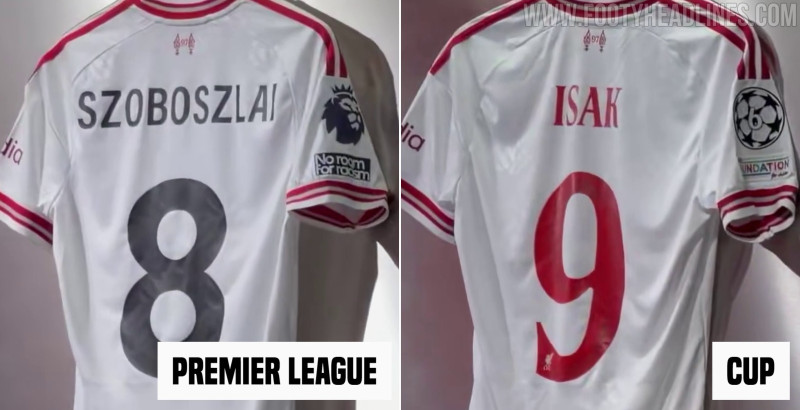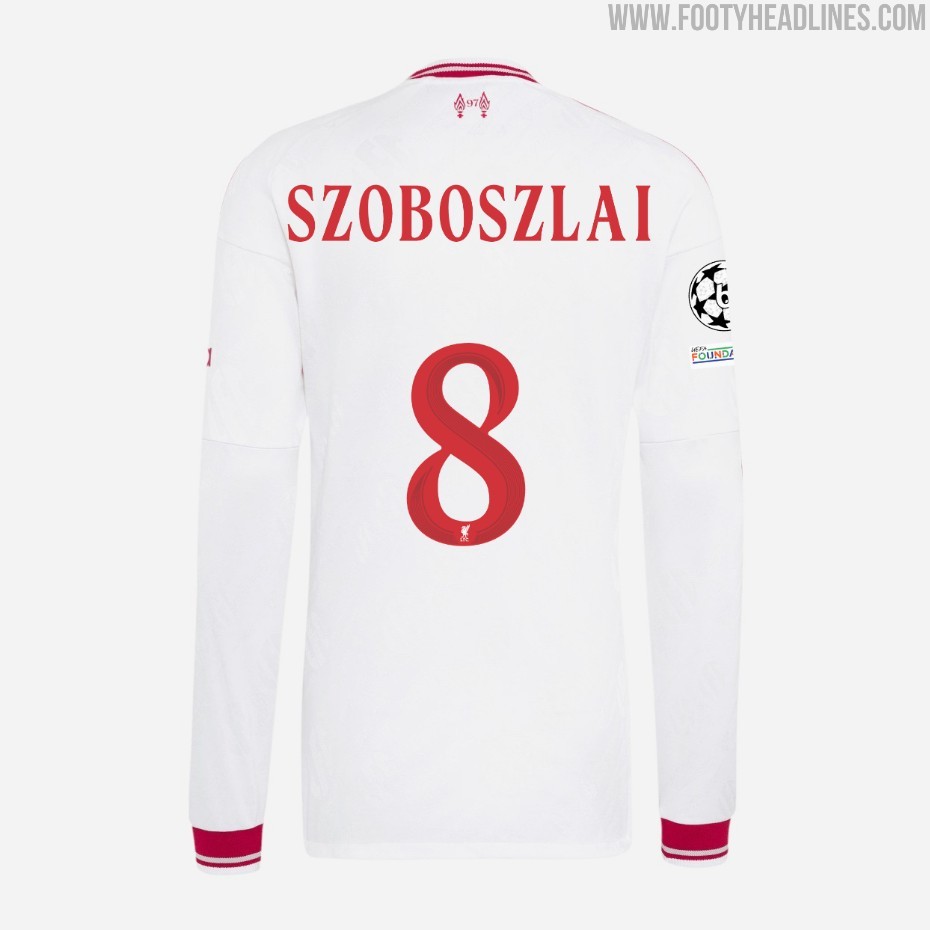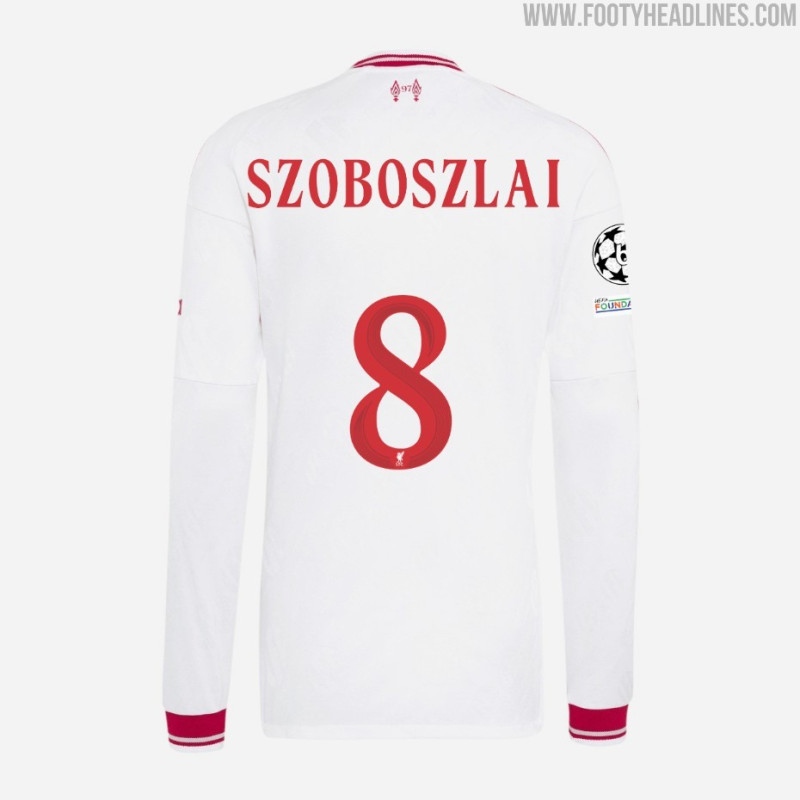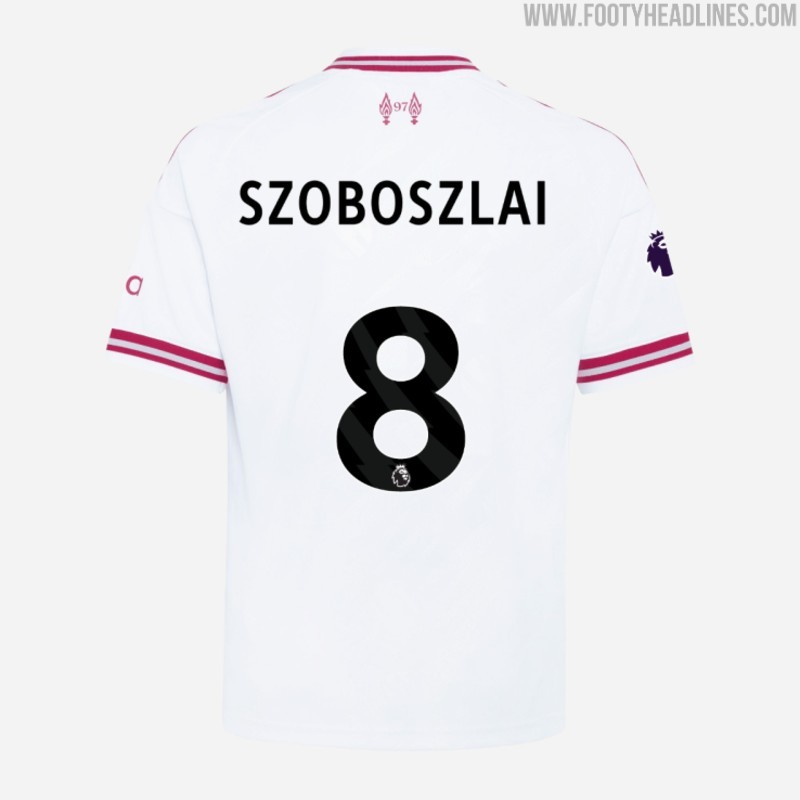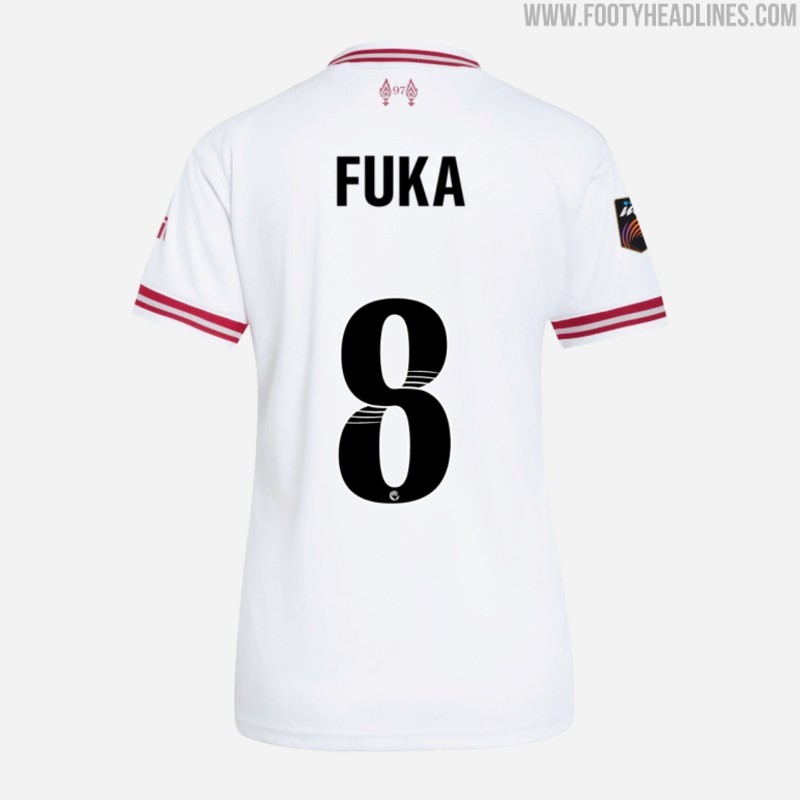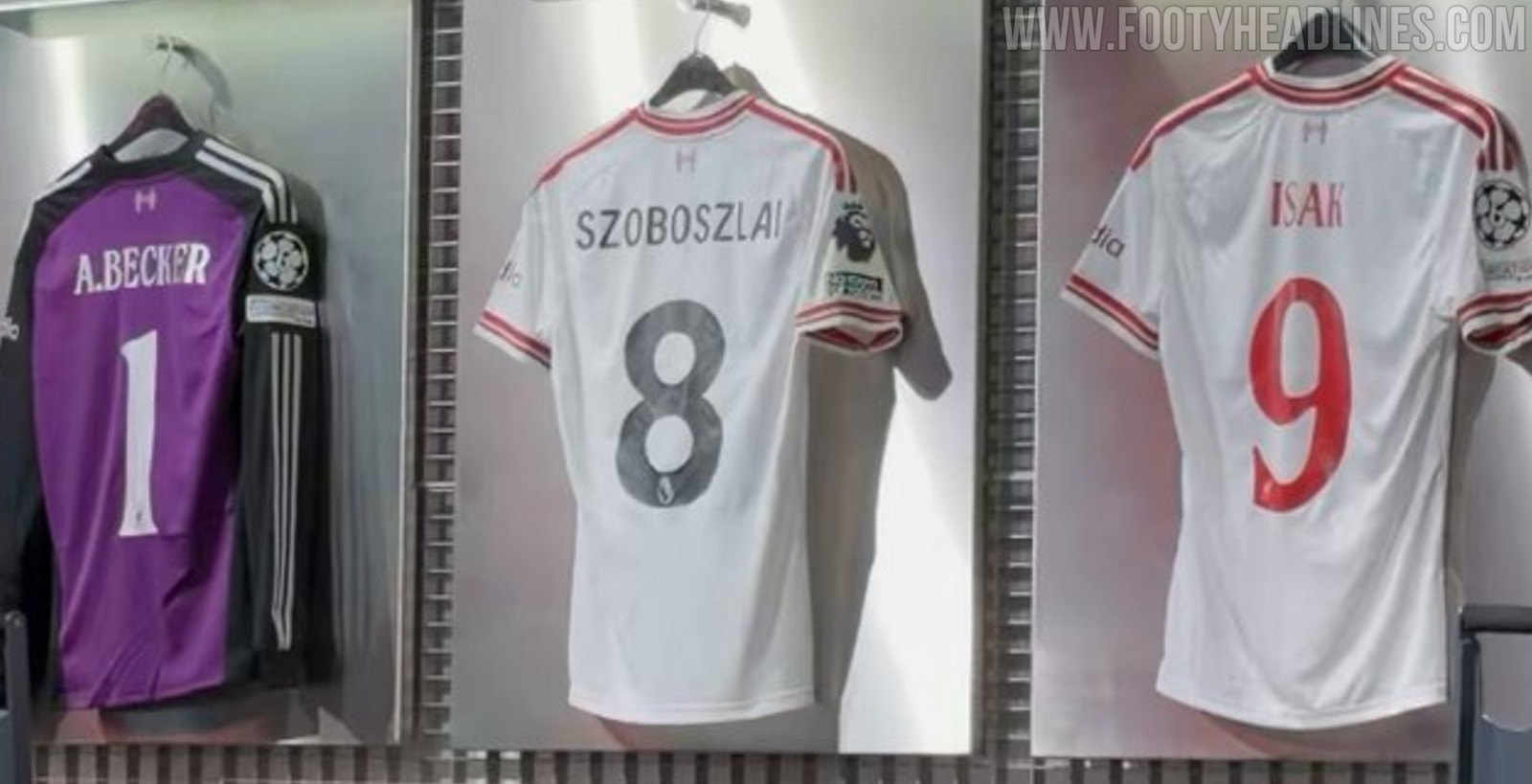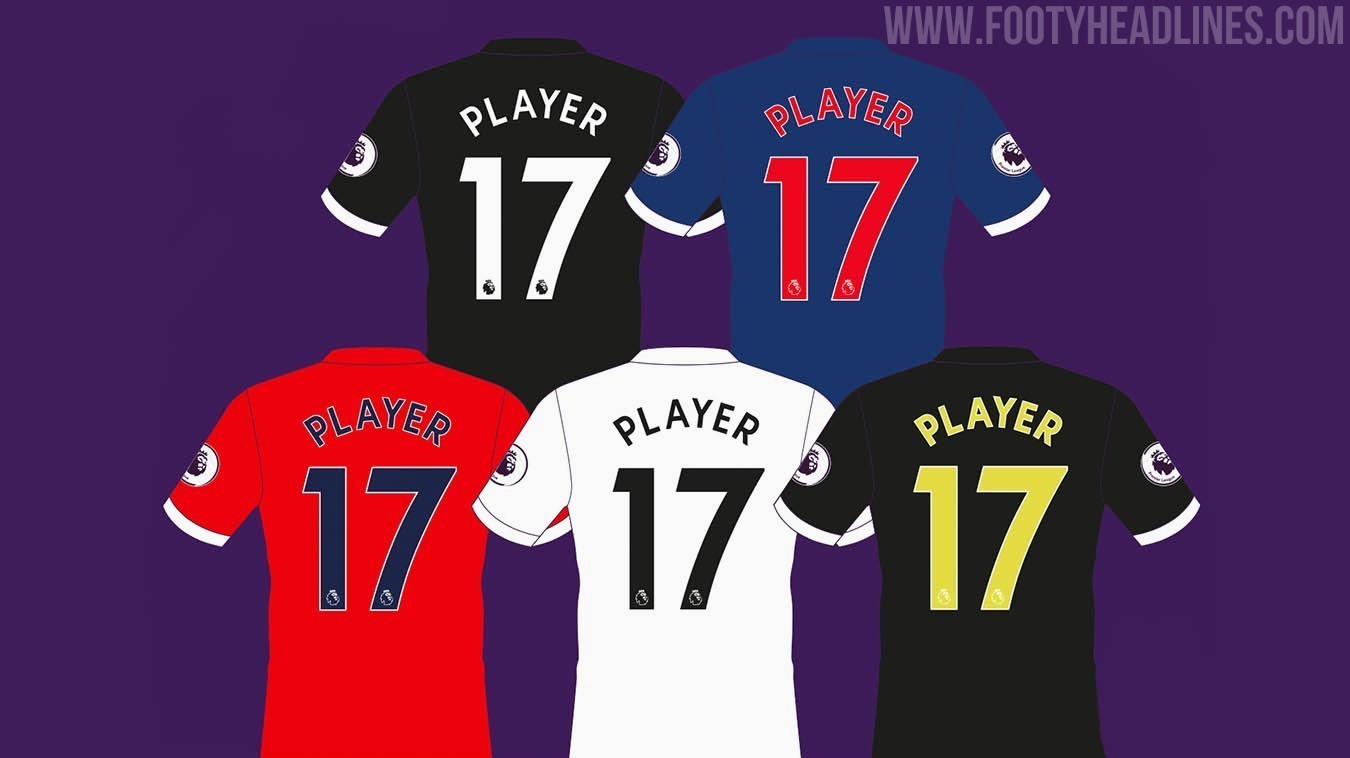
Das Auswärtstrikot von Liverpool für die Saison 26/27 hat eine schwarze Premier-League-Schriftart als Eigenschaft
• Offizielles Auswärtstrikot 26/27: Liverpool hat sein retro-inspiriertes Auswärtstrikot für die Saison 26/27 vorgestellt, das ein klassisches Adidas Trefoil-Logo und das traditionelle „Liver Bird“-Wappen aus den 1980er Jahren zeigt.
• Trikotdesign und Farben: Das Trikotdesign umfasst einen cremefarbenen Grundton, der durch kräftige rote Akzente an Kragen, Schultern und Ärmelbündchen sowie graue Details ergänzt wird.
• Schriftfarbe in der Premier League: Für Premier-League-Spiele wird das Auswärtstrikot schwarze Schriftzüge und Rückennummern tragen, da der rote Farbton der schlanken EPL-Schriftart vom Trikotrot abweicht.
Das Design des Liverpool-Auswärtstrikots 26–27 zeigt einen cremefarbenen Grundton, der durch kräftige rote Akzente an Kragen, Schultern und Ärmelbündchen hervorgehoben wird. Es gibt nur diese beiden Farben, dazu Grau für die Details. Bei Ligaspielen wird das Trikot auf dem Platz jedoch eine vierte Farbe haben.
Bei Premier-League-Spielen hat das Auswärtstrikot von Liverpool für die Saison 2026–2027 schwarze Schriftzüge und Rückennummern – und nicht die rote Variante, die als eine der fünf Voreinstellungen verfügbar ist. Das liegt wahrscheinlich daran, dass die schlanke rote EPL-Schriftart einen anderen Rotton hat als das Trikot. Auch bei der WSL-Version kommt eine schwarze Schrift zum Einsatz.
In Pokalspielen wird Liverpool seine neue Pokalschrift in passendem Rot verwenden. Seltsamerweise wird die Schrift mit dem regulären Liverbird-Logo und dem LFC-Schriftzug geliefert, obwohl das Trikot ein klassisches Logo hat.